Industri film dan hiburan pada era digital ini semakin digemari, mulai banyak bermunculan berbagai platform streaming digital. Mulai dari yang gratis sampai berbayar seperti Netflix. Untuk menarik minat penonton diperlukan desain poster yang menarik dengan cara memilih font yang sesuai dan membuat typography yang unik. Banyak orang yang mencari rekomendasi font berdasarkan poster film terkenal.
Salah satu elemen penting dalam penggunaan font adalah menciptakan kesan yang menarik perhatian dan membawa pesan yang kuat. Font yang digunakan dalam poster film dapat memberikan dampak besar terhadap kesan dan emosi kepada penonton. Artikel ini akan membahas 7 font dari film terkenal sebagai rekomendasi dan menjelaskan jenis tipografi sering ditemui dalam poster film dan dunia hiburan.
1. “The Greatest Showman”
Film “The Greatest Showman” adalah film musikal yang menceritakan kisah P.T Barnum dan pertunjukan sirkusnya bersama orang-orang unik yang dikucilkan oleh masyarakat. kisah P.T Barnum yang bangkit dari nol untuk menciptakan tontonan yang menjadi favorit di seluruh dunia.
Font : Trajan
Font yang digunakan dalam poster film The Greatest Showman adalah Trajan. Trajan sering digunakan untuk menciptakan suasana klasik yang megah, sesuai dengan tema cerita dengan film sirkus spektakuler ini.
Terdapat pula font tiruan yang sudah disesuaikan dengan poster film yaitu the greatest font by FZ font. Bagi kamu yang ingin membuat desain yang terinspirasi dari film tersebut dapat menggunakan font ini.
Beberapa font yang mirip seperti di film The greatest Showman yaitu lemon milk, fantasy magic, dragon EF italic, Dengan sedikit penyesuaian gradasi dan tipografi akan sangat mirip dengan font seperti dalam film tersebut.
2. “Cruella”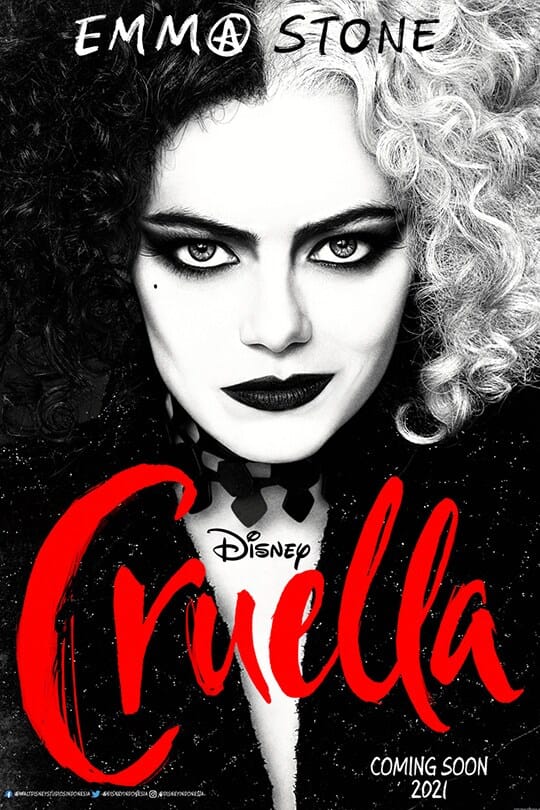
Film Cruella menceritakan transformasi tokoh Estella menjadi Cruella De Vil. Seorang gadis berbakat bercita-cita menjadi desainer terkenal. Impian tersebut sempat kandas hingga dia menjadi pencuri bersama kedua rekannya. saat bekerja dengan desainer terkenal Cruella menemukan fakta tentang ibunya dan berencana melakukan balas dendam.
Font : abdullah font
Font yang digunakan dalam film ini adalah tipe font brush. Film ini menggunakan font yang di desain khusus. Rekomendasi font yang mirip seperti yang digunakan dalam film Cruella adalah Abdullah font, sedikit perubahan desain akan cukup mirip dan memberikan kesan misterius seperti sosok Cruella.
3. “Barbie”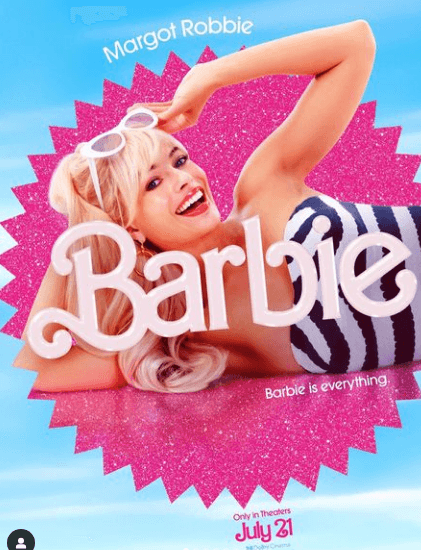
Film versi live action Barbie ini mengisahkan tentang kehidupan para Barbie di Barbie Land dengan berbagai karakter yang berbeda-beda, seperti dalam versi animasinya Barbie memiliki berbagai profesi dan karakter.
Di dunia Barbie para pria ini memiliki nama Ken. Kehidupan para Barbie di pulaunya sangat damai dan penuh warna hingga Barbie pergi dunia manusia dan kemudian menyadari banyak hal.
Font : barbie medium
Baik dalam versi animasi maupun filmnya, Film Barbie menggunakan font “barbie medium”. Font resmi milik barbie ini sering digunakan dalam semua produk barbie baik film maupun merchandise yang dirilis termasuk animasinya. Rekomendasi penggunaan font ini pada desain dengan konsep yang ceria seperti karakter Barbie.
4. “Squid Game”
Series Squid Game in menceritakan permainan berdarah yang berhadiah fantastis. Orang-orang dalam series ini bertahan hidup dengan cara melakukan berbagai permainan misterius.
Font: game of squid
Font game of squid ini dibuat oleh Darell Flood yang terinspirasi dari series squid game. Squid Game sendiri memiliki lettering yang unik, dalam poster tersebut. Terdapat simbol bulat, segitiga dan kotak dalam judul posternya yang berhubungan dengan isi cerita seriesnya.
5. “Avatar”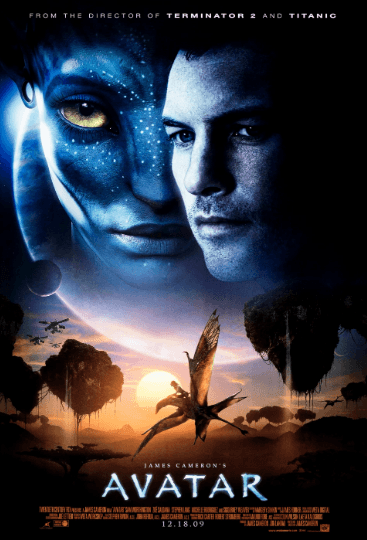
Film Avatar menceritakan tentang Jake Sully seorang manusia yang menjadi Avatar spesies humanoid di planet pandora yang memiliki sumber daya alam yang melimpah. Seiring berjalannya waktu dia bimbang apakah melindungi bangsa asli planet itu atau setia kepada manusia. Film ini juga baru saja merilis seri kedua loh yaitu The Way Of Water.
Font : Papyrus
Film Avatar menggunakan font Papyrus oleh Chris Costello. Font ini memberikan kesan misterius dari semesta Avatar yang unik. Font Lain yang juga mirip dengan bisa kamu gunakan sebagai referensi saat membuat desain yaitu Film Cryptic, Plato, Monotonia Display, dan Humana Sans ITC.
6. “Eternals”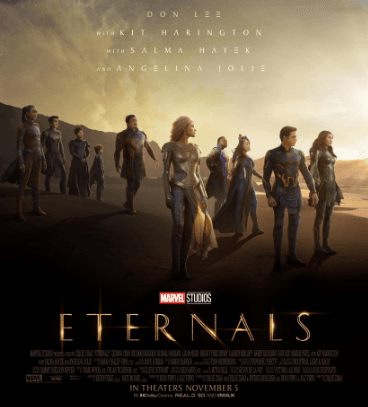
Film superhero yang diproduksi Marvel berjudul Eternals ini masih satu universe dengan Avengers. Film ini berlatar waktu setelah film peristiwa Endgame menceritakan tentang orang-orang yang berkekuatan super yang diutus membantu peradaban manusia bumi sekaligus melindungi mereka dari ancaman deviants.
Font : Lubalin Graph
Dalam poster film eternals ini menggunakan font Lubalin Graph. Font dalam film ini menciptakan kesan modern namun unik dan klasik. Kamu bisa menggunakan font ini untuk menghasilkan desain yang modern dan futuristik.
7. “Stranger Things”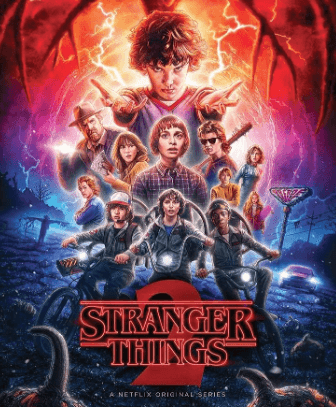
Cerita series ini berawal dari hilangnya seorang anak bernama Will. Dalam proses menemukan Will teman-teman dan kerabatnya mengalami runtunan kejadian aneh dan mistis yang membawa mereka bertemu seorang gadis yang terlibat organisasi misterius.
Font : ITC Benguiat
Dalam poster judul series ini menggunakan font ITC Benguiat yang memberikan kesan misterius dan aneh. Selain Seriesnya yang bernuansa tahun 1980, font yang digunakan juga memberi nuansa retro tahun 1980-an. Font ini banyak digunakan dalam desain film dan komik pada tahun itu, sehingga menambah suasana nostalgia.
Jenis Tipografi yang Sering Digunakan dalam Film:
Tipografi adalah Variasi dalam menata, memilih dan mengatur huruf agar lebih menarik. Berbeda dengan Lettering yang mendesain huruf dengan manual, disesuaikan dengan kebutuhan seperti kebutuhan dalam poster film untuk memberikan hal yang berbeda dan unik dari font yang sudah ada. Keduanya dibutuhkan untuk menciptakan kesan dan karakter tertentu.
- Serif: Salah satu Jenis font yang memiliki dekorasi tambahan di ujung huruf, seperti “Times New Roman.” Font ini biasanya dipakai dalam film dengan tema fantasi atau klasik. Contohnya seperti dalam film The Godfather.
- Sans-Serif: Font ini tidak memiliki tambahan di ujung huruf, seperti “Helvetica.” Sans-serif sering ditemukan dalam film dengan tema yang modern dan bersih. Contohnya seperti dalam film The Matrix.
- Display: Font yang dibuat khusus untuk memikat yang melihatnya, seperti “Bebas Neue.” Font display ini kerap dipakai untuk memberikan kesan dramatis pada poster film. Contohnya seperti dalam film
- Script: Font yang dibuat mirip seperti tulisan tangan, seperti “Amelie.” Font script kerap digunakan dalam film yang memiliki nuansa romantis. Contohnya seperti dalam film Amelie.
- Monospace: Font ini memiliki jarak antar hurufnya seperti “Courier New.” Monospace sering dipakai dalam poster film yang tentang teknologi atau keamanan.
Dalam dunia hiburan, penggunaan font dan tipografi adalah seni yang kuat. Memilih font yang tepat dapat membantu menciptakan kesan yang kuat dan memikat penonton ke dalam cerita film. Semoga artikel ini memberikan wawasan tentang bagaimana font memengaruhi kesan visual dalam dunia hiburan.